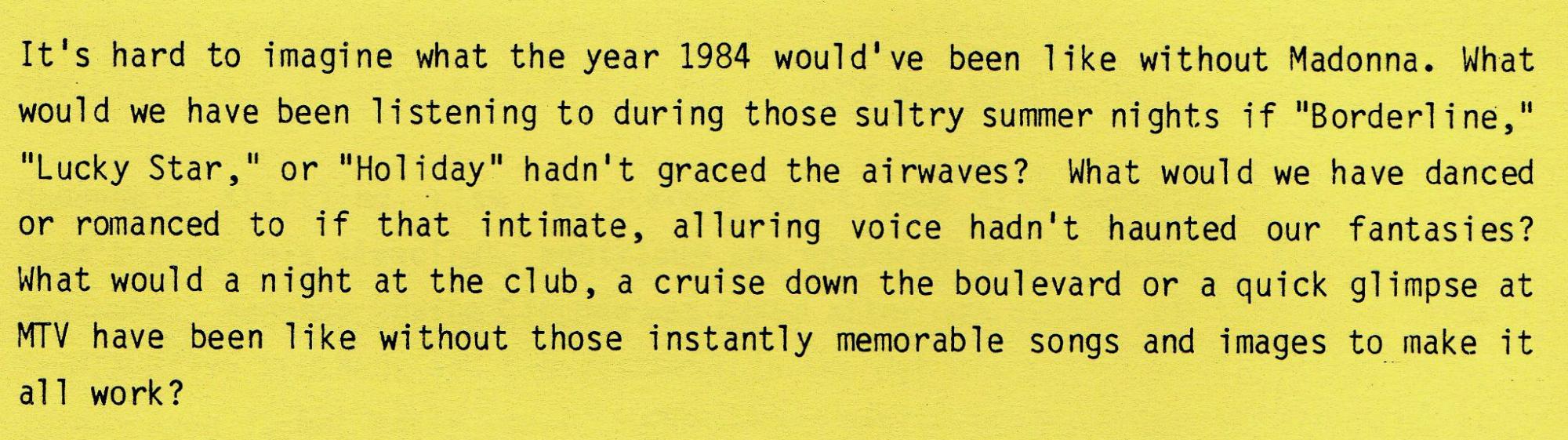
Suche Schrift dieser Presseinformation von Warner Bros. Records aus den 1980er Jahren
Hat jemand eine Idee, welche Schriftart hier genau verwendet wird? Es handelt sich um eine beispielhafte Presseinformation von Warner Bros. Records aus den USA aus dem Jahr 1984. Ich denke, es ist vermutlich eine Schreibmaschinenschriftart, wenn es denn 1984 bereits elektronische Schreibmaschinen gab, die Blocksatz beherrschten?
1984 gab es sogar schon Schreibmaschinen mit Tintenstrahlwerk (Olympia 1011) und Thermotransfermaschinen (IBM 6750), die Blocksatz beherrschten.
In deinem Beispiel wird eine "Letter Gothic" verwendet, 1956 von Roger Roberson für die elektrischen IBM-Modelle entworfen. Die Kugelkopfmaschine IBM Selectric ab Anfang der 1960er Jahre machte die Letter Gothic weltberühmt und -verbreitet.
Mein Onkel arbeitete von den 60ern bis in die 80er Jahre bei Olympia (wir stammen aus Wilhelmshaven). Er war in den späten 70ern nach Hong Kong abgestellt, und erzählte uns über das Problem, Schreibmaschinen für den chinesischen Markt herzustellen. Bei über 1500 Zeichen war der herkömmliche Weg ausgeschlossen, und so arbeitete Olympia an einem System, das mikroskopische Tintenkleckse auf das Papier spritzt, um so die Zeichen herzustellen. "Was für'n Blödsinn!" sagte ich.  "Ihr habt doch immer noch ein Problem mit 1500 Tasten!"